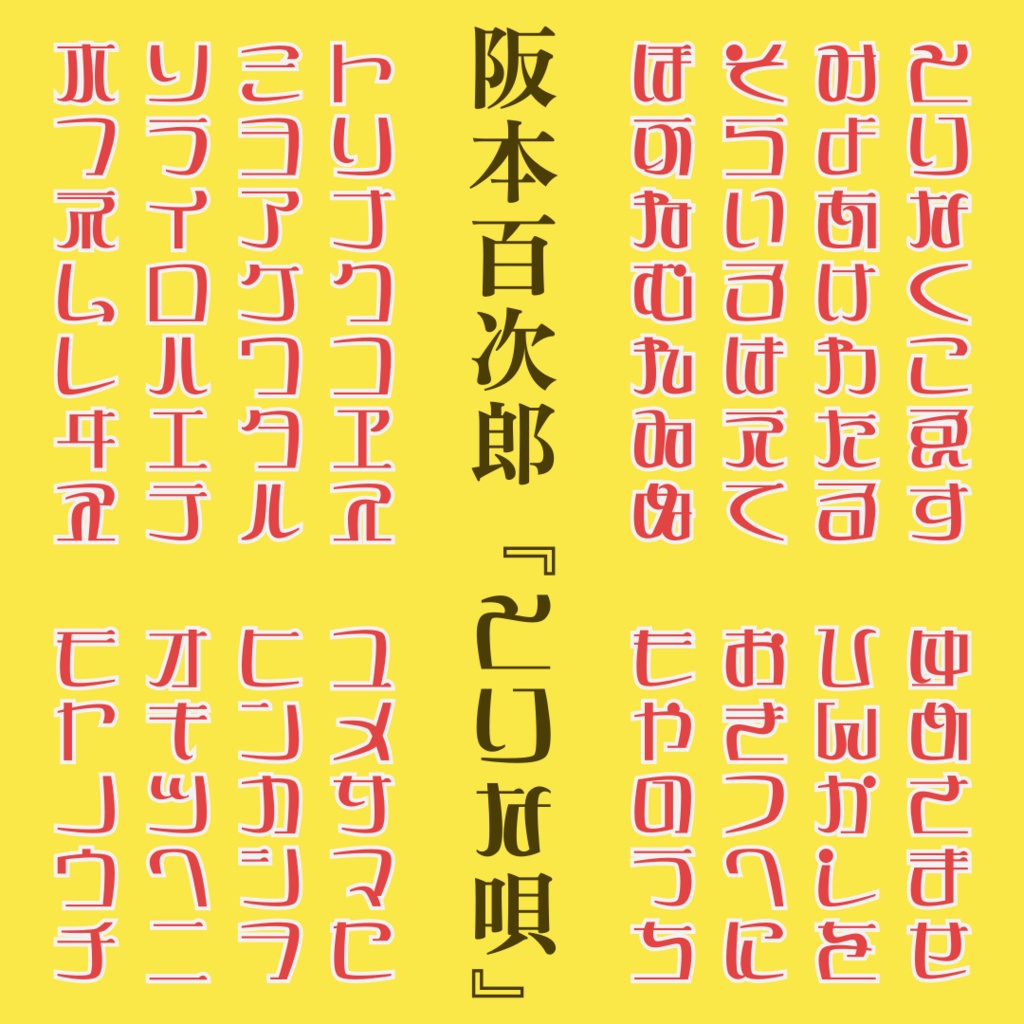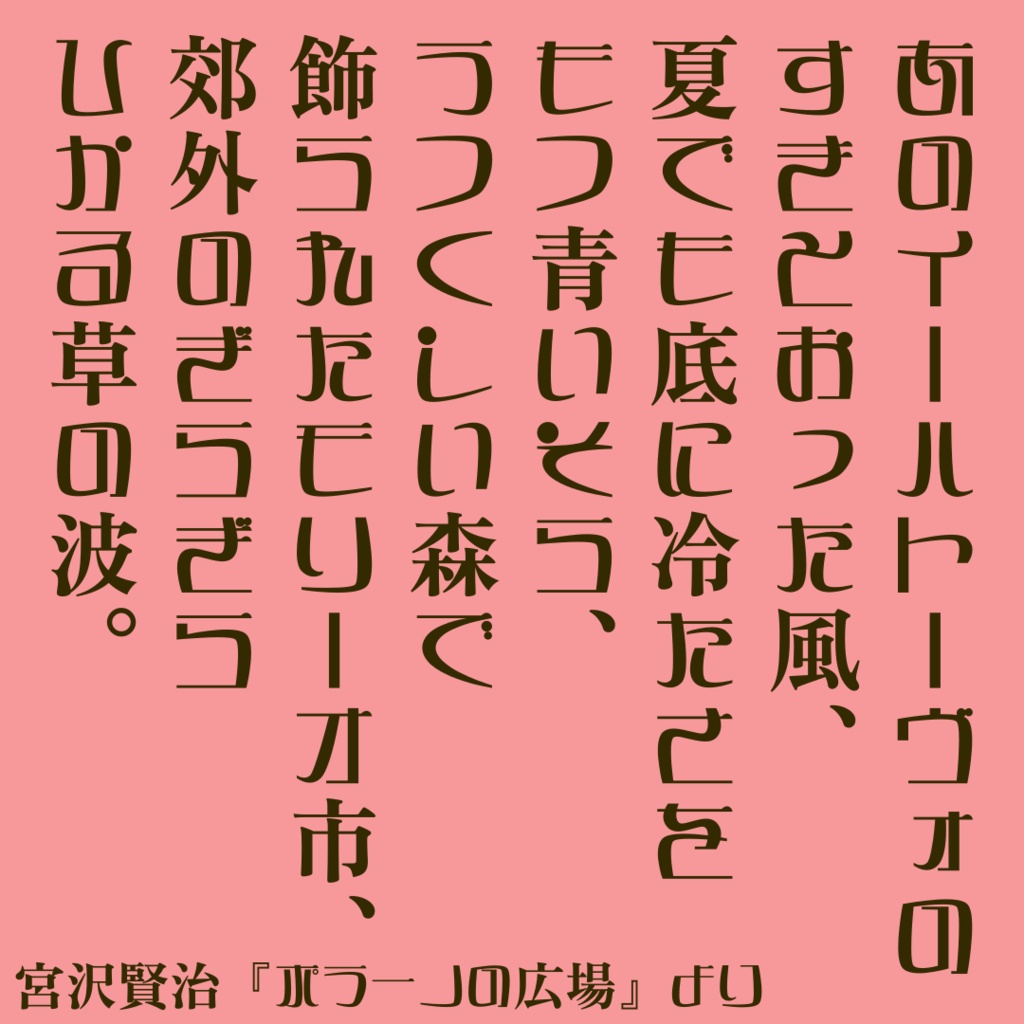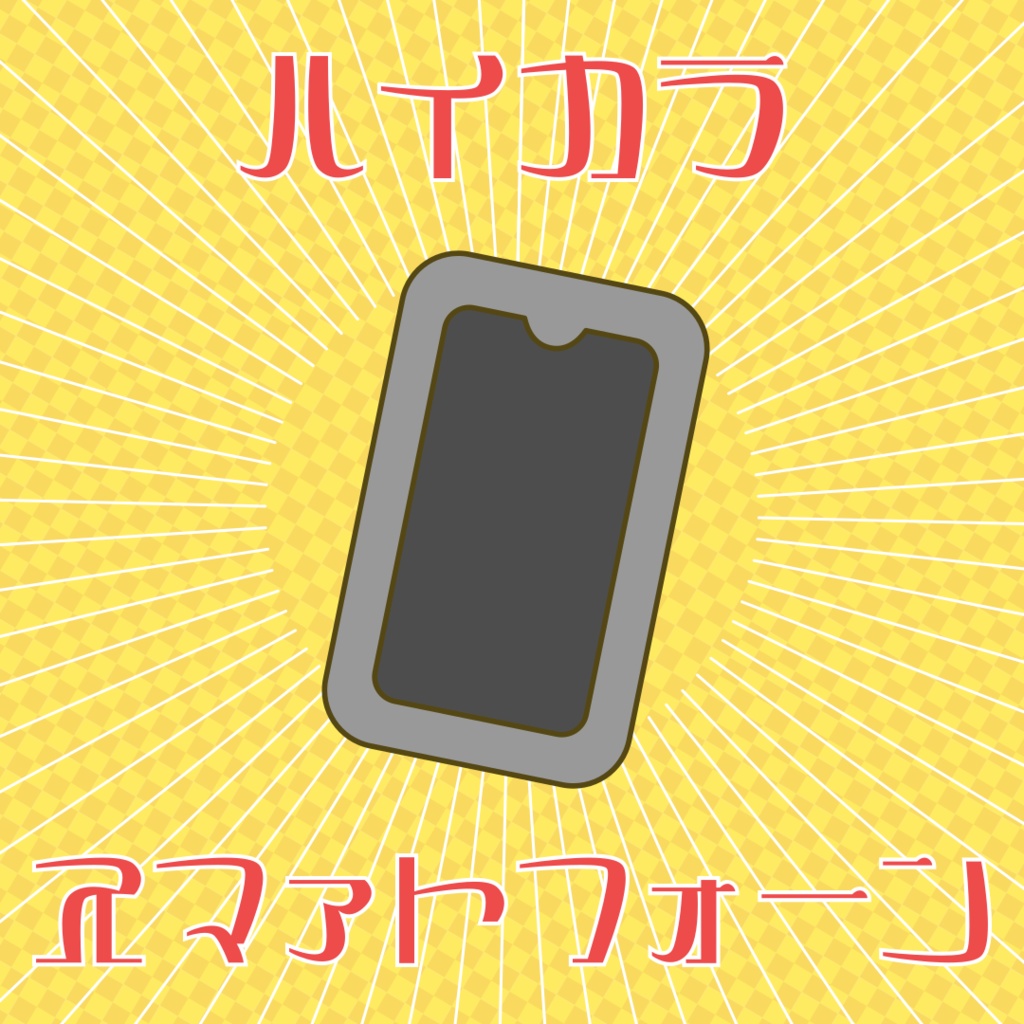
【フリーフォント】SY図あミン
【概要】 図あミンは、大正から昭和初期にデザインされた「図案文字」を参考にした仮名と、明朝体の漢字を組み合わせたデザイン書体です。 【規約】 SIL Open Font License 1.1で配布しているので、ライセンスの範囲内でご自由にお使いいただけます。 縦書き可、商用利用可、再配布・改変可。詳しくはライセンスをよく読んでください。 以下はSIL Open Font License 1.1の日本語参考訳のURLです。 https://licenses.opensource.jp/OFL-1.1/OFL-1.1.html 【謝辞】 仮名以外の部分に、Zen Old Mincho Blackを使わせていただきました。 デザイナーである大平善道様、およびGoogle Fonts様にこの場を借りてお礼申し上げます。ありがとうございます。 https://fonts.google.com/specimen/Zen+Old+Mincho